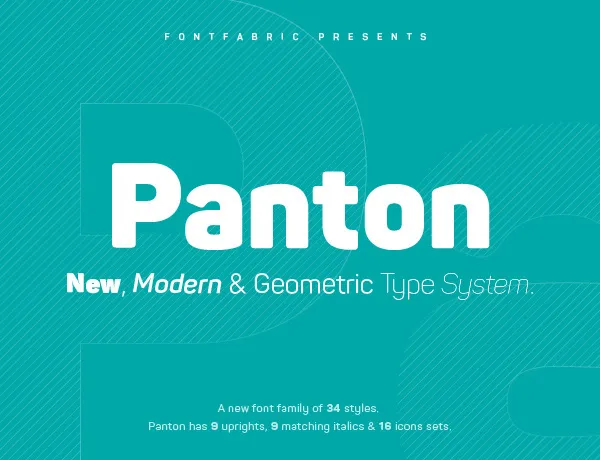
A Panton Typeface é uma famosa família de fontes sans serif que abrange 34 pesos, incluindo sete tipos uprights com nove itálicos e dezesseis conjuntos de ícones como um convidativo bonus. Esta fonte é projetada para oferecer excelente legibilidade tanto na web quanto em impressão, além de designs geométricos bem acabados, otimização da justificação (kerning) e uma excelente performance tanto no formato-fonte para a web quanto em sua legibilidade geral. A Panton é uma fonte perfeita para designers que buscam uma combinação única de modernidade e eficiência, garantindo um design elegante e profissional que se adequa a diversos usos, desde logotipos até o estilização de sites e materiais gráficos.